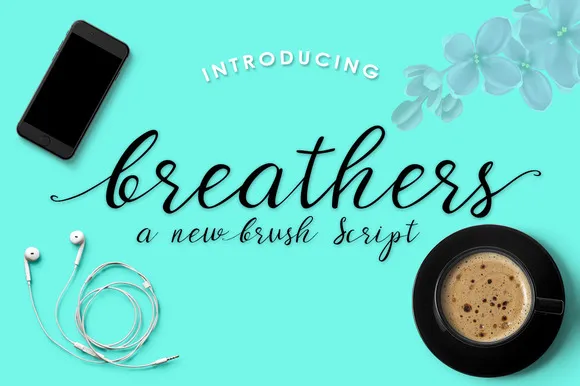
Breathers Script Font – Download Grátis
A Breathers Script Font é uma elegante escolha para quem busca um equilíbrio entre modernidade e sofisticação. Essa fonte manuscrita oferece um toque romântico, ideal tanto para criar marcas de marca ou decorar qualquer projeto visual como para cartas de casamento ou blog. Ela é perfeitamente adaptada para os requisitos de design que exigem elegância e simplicidade. Essa fonte também é ótima para criar logomarcas, belas molduras para a sua casa ou até mesmo para aplicativos de negócios, como pequenos anúncios ou capas de livros. Sem dúvida, ela se destaca em qualquer tipo de projeto visual que você desejar explorar com esta fonte exclusiva.
Designer: Gfont